長城(Great Wall)
「長城字體」的版權方「中國長城計算機集團公司」於 1988 年成立,1997 年通過資產重組設立「中國長城科技集團股份有限公司」(2017 年重新整合),為中國電子信息產業集團有限公司(CEC)旗下子集團,以計算機業務為主(包括電腦整機、外設、電源等)。據企查查,原「中國長城計算機集團公司」現名為「中電長城計算機集團有限公司」,同屬中國電子(CEC),存續。長城前後共發佈字體數十款,但字體並非其主要業務,僅作為附屬產品。現該業務已無人負責,其字庫已廢棄,然而其《仿宋 GB2312》《楷體 GB2312》迄今仍在公文等領域廣泛應用。
本文將長城字體分為四個部分進行介紹。
1. Windows XP 內置的仿宋、楷體
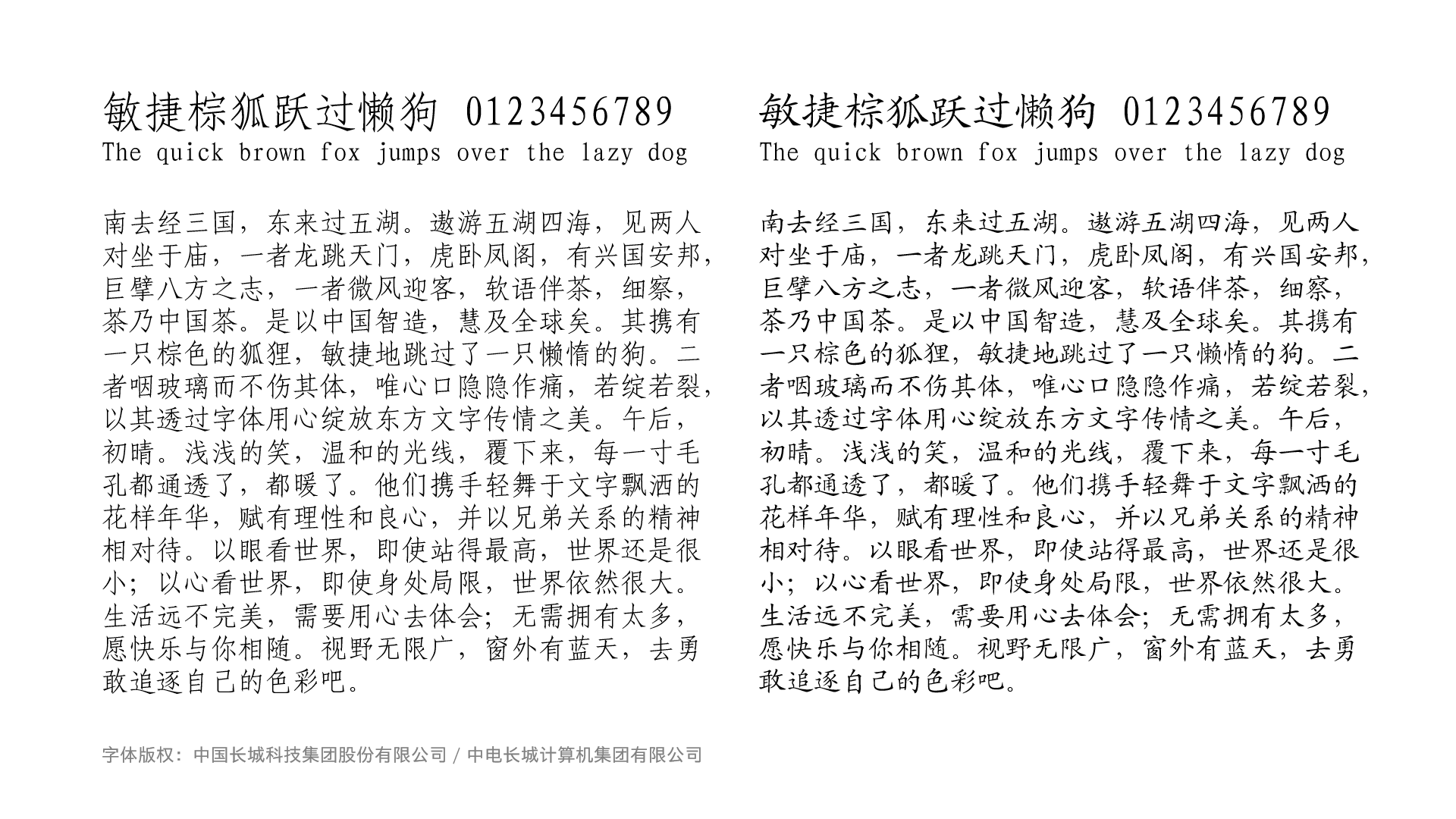
這兩款字體就不用過多介紹了,兼容性最高,至今仍有一些單位和個人習慣了這兩款本該淘汰的字體(可能是因為跟中易的仿楷比起來,這兩款仿楷看着更加「順眼」?),而且由於是筆畫分離字體,這兩款字體在新版本 Word 中加粗時會有部分輪廓反向加粗,且列印後也可能會出現這種情況(下圖為列印在紙上的效果)。
值得一提的是這兩款字體看似嵌入了點陣,可惜在 FontForge 裏讀取不出來(Windows 95、98 內置的仿宋和楷體則沒有「嵌入點陣」的效果)。
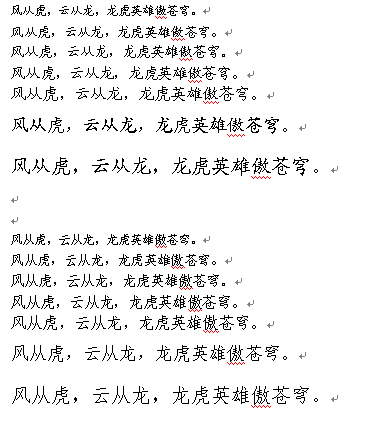
(編輯:這兩款字體嵌入的點陣可在 TTEdit 中讀取,詳見知乎文章。)
2. Windows 3.2 內置的宋體、黑體
Windows 3.2 是微軟針對中國大陸市場推出的特供版 Windows,內置了長城宋體和黑體,以上海字為藍本,採用 GB 2312 字符集,且同樣為筆畫分離字體。這兩款字體在較新版本的 Windows 中無法正常打開。
另外需要說明的一點是,這兩款字體 TTF 本身不嵌點陣,點陣數據在 Windows 3.2 中以 SIMSUNxx.FON 的形式存儲於 TTF 之外。
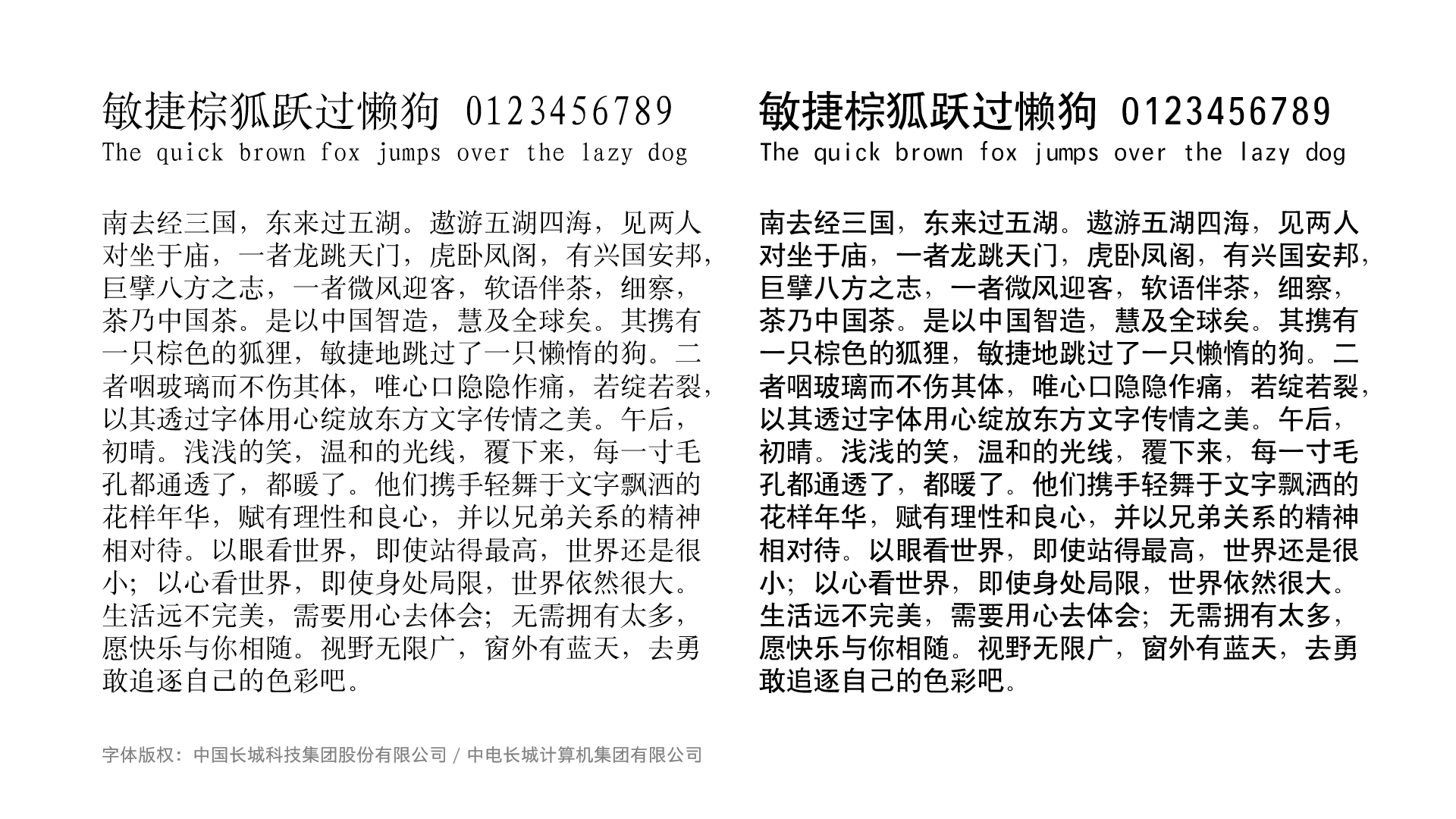
(順帶一提,Windows 3.1 簡中版內置的是 CompuFont 的宋體和黑體,彼時 CompuFont 已被華康收購,這兩款字體也是華康簡體宋、黑體的原型,不屬於本文 abandonfont 範疇。)
3. 《長城全真字庫》4 款字體,以及「崑崙」系列字體
1994 年,長城推出了「長城全真字庫」軟件,包含了四款簡體中文字體:長城楷體、長城仿宋、長城粗隸書、長城細圓,作為 Windows 3.1 / 3.2 內置中文字體的補充。
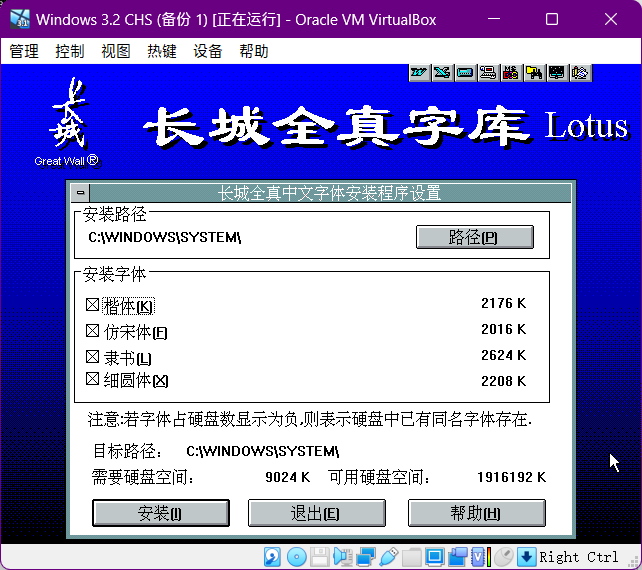
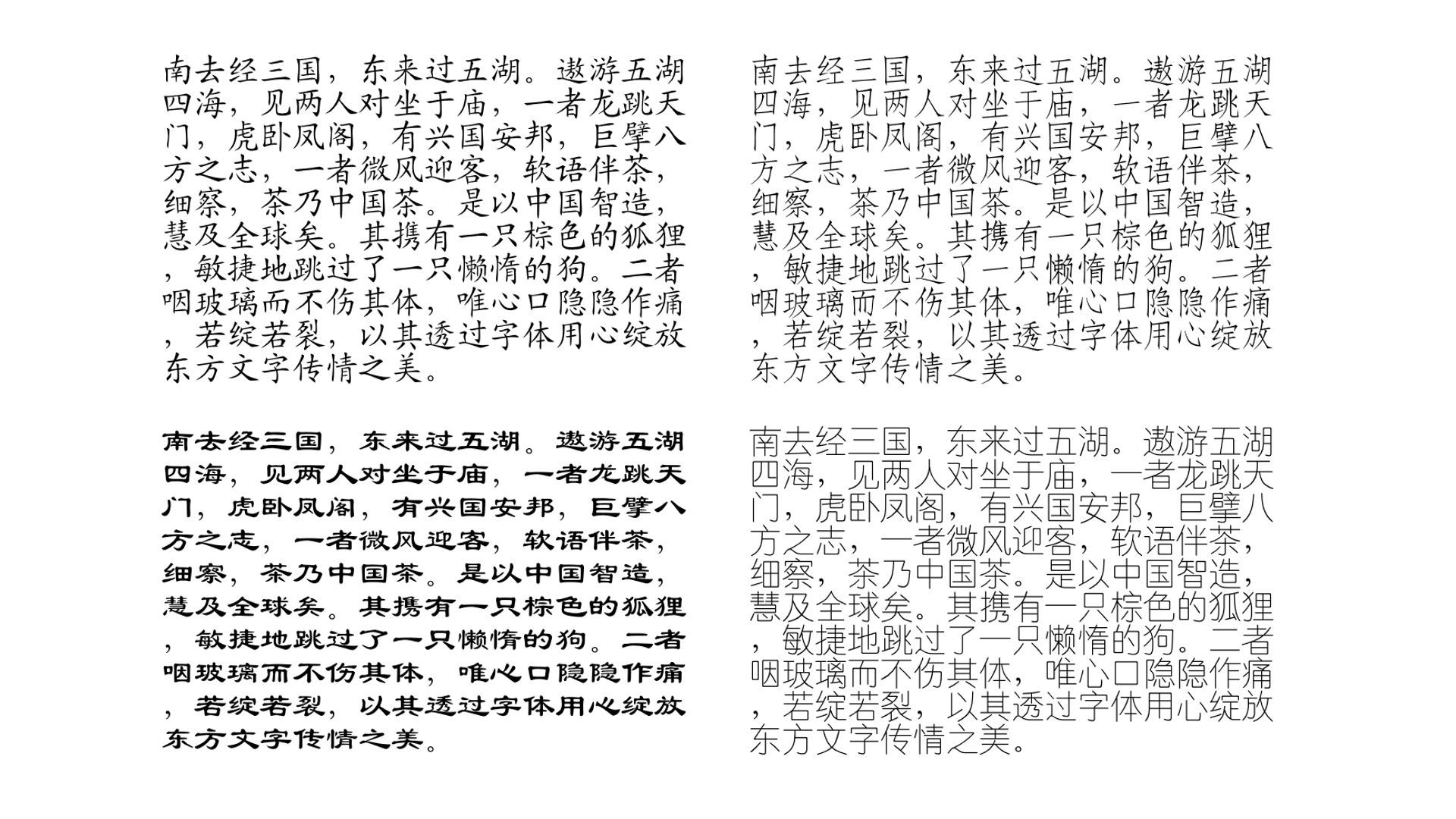
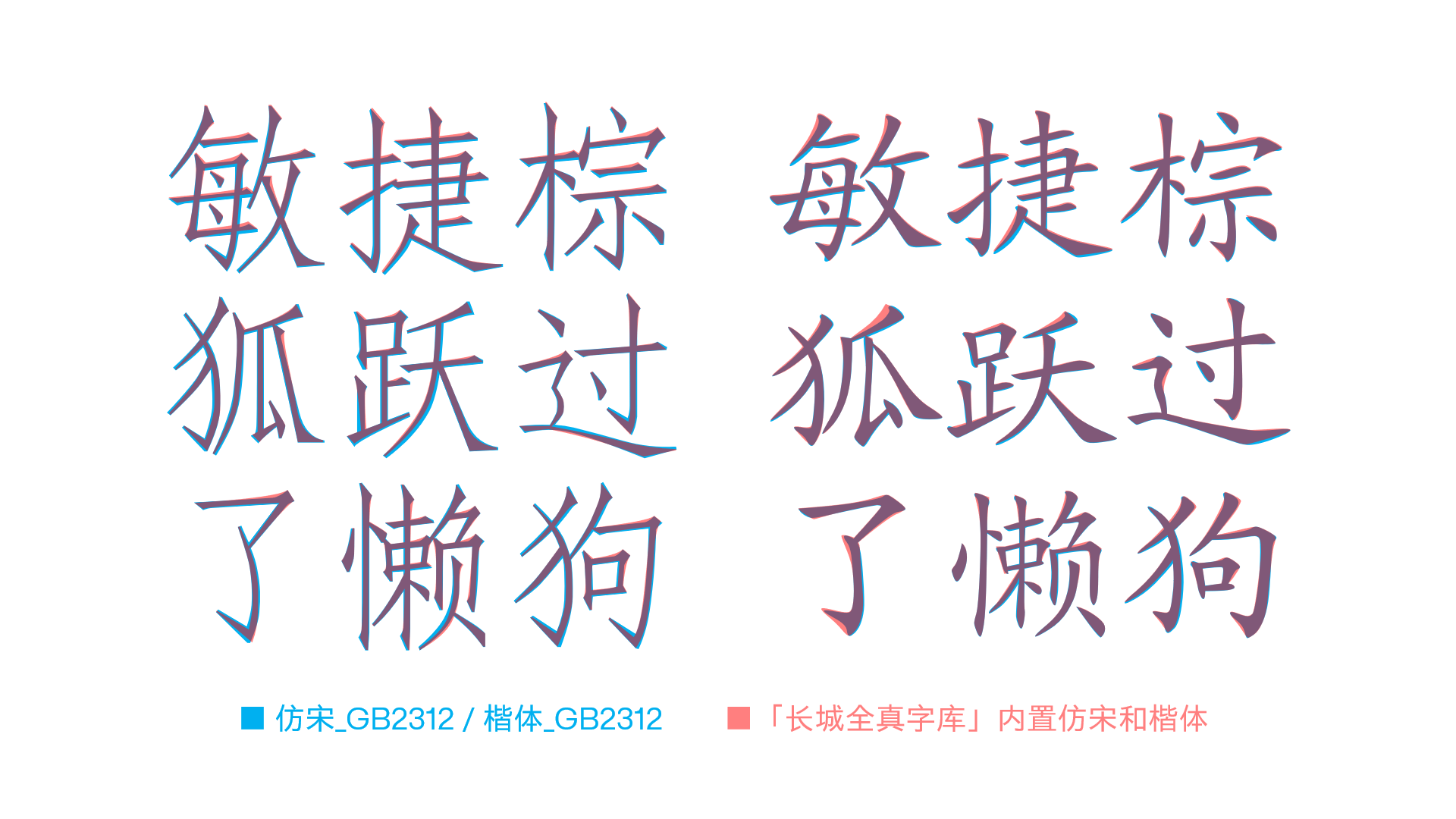
另外在網上也能找到「崑崙」系列字體,也包含這四款字體外加「崑崙宋體」,版權方為「北京崑崙電子印刷技術公司」,其股東為中電長城,目前已吊銷。
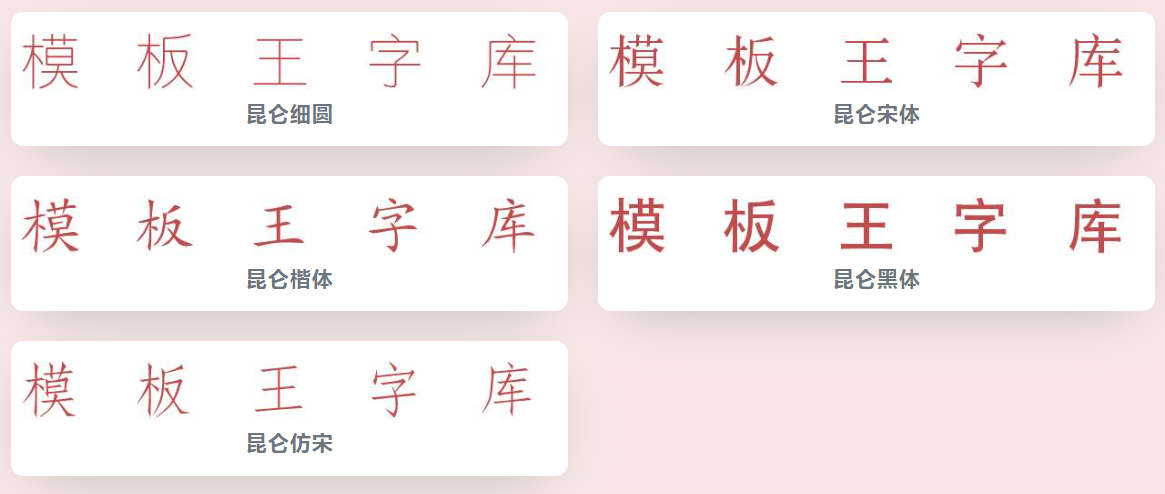
無論是長城全真字庫,還是崑崙字體,在現在看來這些字體的輪廓比較簡單粗放,包括前面提到的 Windows 3.2 內置的宋體、黑體也是如此。後來的「長城字體合集」中對字體輪廓作了優化。
另外說到崑崙,這家公司也於 2002 年推出了「彩虹」系列字體,包含黑體、小標宋、楷體、粗仿宋,雖然從字體包含字符數量來看字庫為 GBK,但實際上只支持 GB 2312(下圖為「彩虹小標宋」,採用了上海宋的骨架)。
4. 網上流傳的「長城字庫全套 46 款字體」
重量級來了。這個字體合集流傳甚廣,可以在很多所謂的「字體免費下載站」中下載到它們。
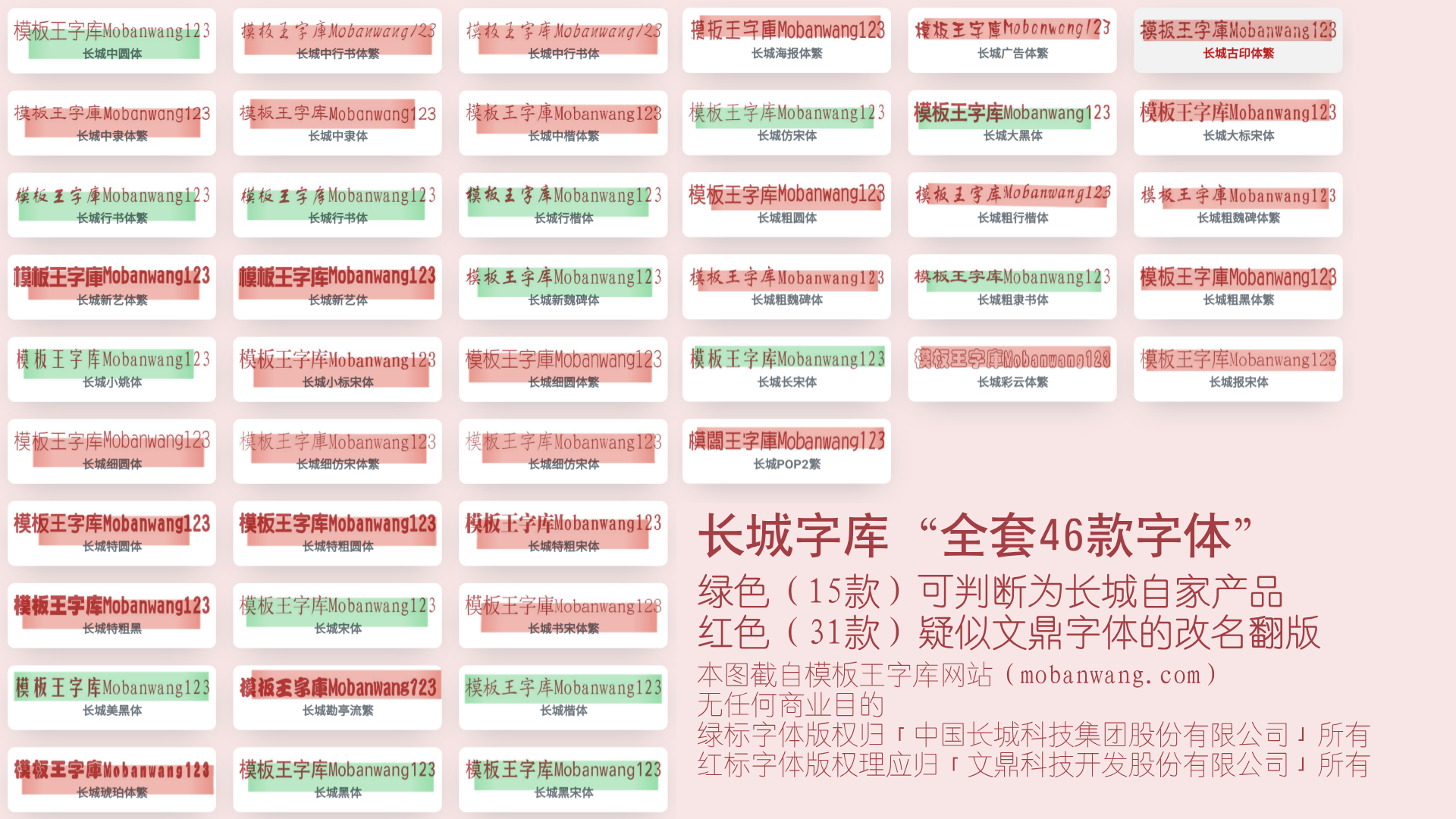
在這 46 款字體中,有 15 款字體可判斷是長城自家的字體(從一脈相承的西文部分可以看出),這裡面包含了與 Windows 3.2 內置或「長城全真字庫」包含的版本相比輪廓有所優化的宋體、黑體、楷體、仿宋、粗隸書(但不包含「長城全真字庫」中出現的細圓體,倒是有中圓體),也包含了大黑、宋黑、中圓、長宋、行楷、新魏、小姚、美黑、行書、行書繁等其他字體,且這 15 款字體中大多筆畫分離(不過「長城美黑」的輪廓有些奇怪,而且收字也不全)。在這 15 款字體中,「長城行楷」為任(政)體行楷,「長城行書」為舒(同)體行書,且「長城行書繁」是這 15 款字體裏唯一的偽繁字體。
下圖為這套合集裏「長城宋體」「長城黑體」與 Windows 3.2 內置宋體、黑體的比對。
甚至在 2025 年,也仍然有人在用長城宋體(下圖攝於鄭州中原區華山 121 文創園)
至於「仿宋 GB2312」「楷體 GB2312」與合集中的「長城仿宋體」「長城楷體」,前者與後者在字形輪廓上完全重合,因此不作比對圖。
其餘的 31 款字體經比對,均可判斷為文鼎字體的改名翻版,不屬於本文 abandonfont 範疇,這裏不作介紹。